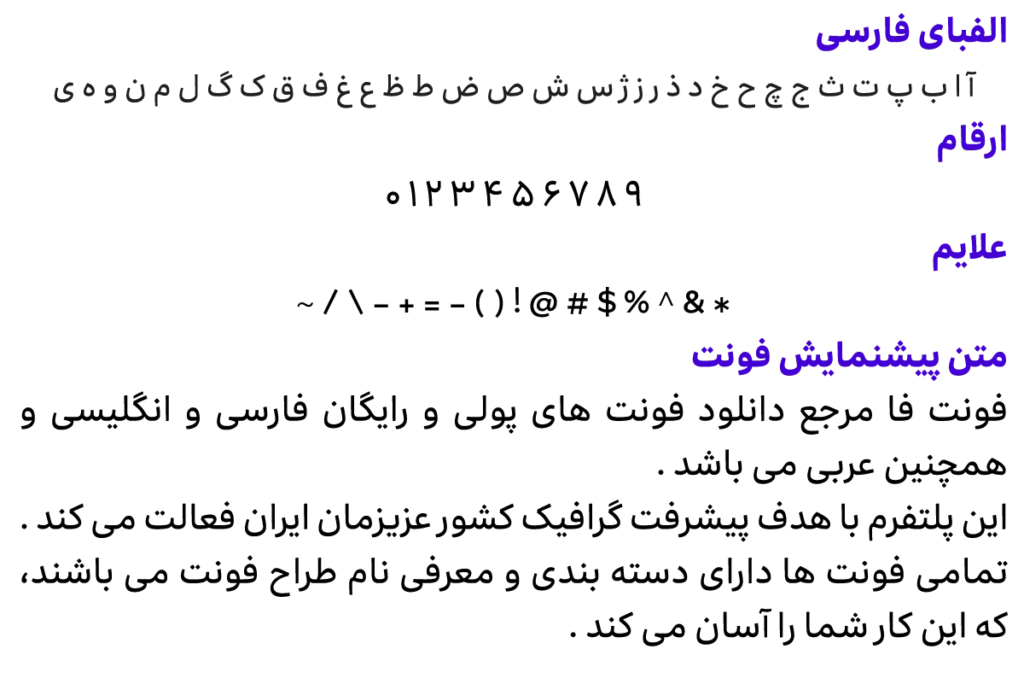
فونت فارسی ایرانسل – MTN Irancell
طراح فونت: امین عابدی نوع فونت: فونت عنوان و فونت متن
توضیحات و معرفی فونت ایرانسل
فونت فارسی ایرانسل ( MTN Irancell ) از مجموعه فونت های آزاد و برتر می باشد، همچنان نوع فونت عنوان و متن می باشد.
از این تایپ فیس می توانید در طراحی های که میخواهید جلو زیبایی به اثر خود بدهید استفاده کنید.
همچنان این فونت در 6 وزن سنگین و پر رنگ و نیمه پر رنگ و سبک و متوسط و فوق سبک است.
در لیست زیر می توانید وزن های این فونت شگفت انگیز و زیبا را ببینید.